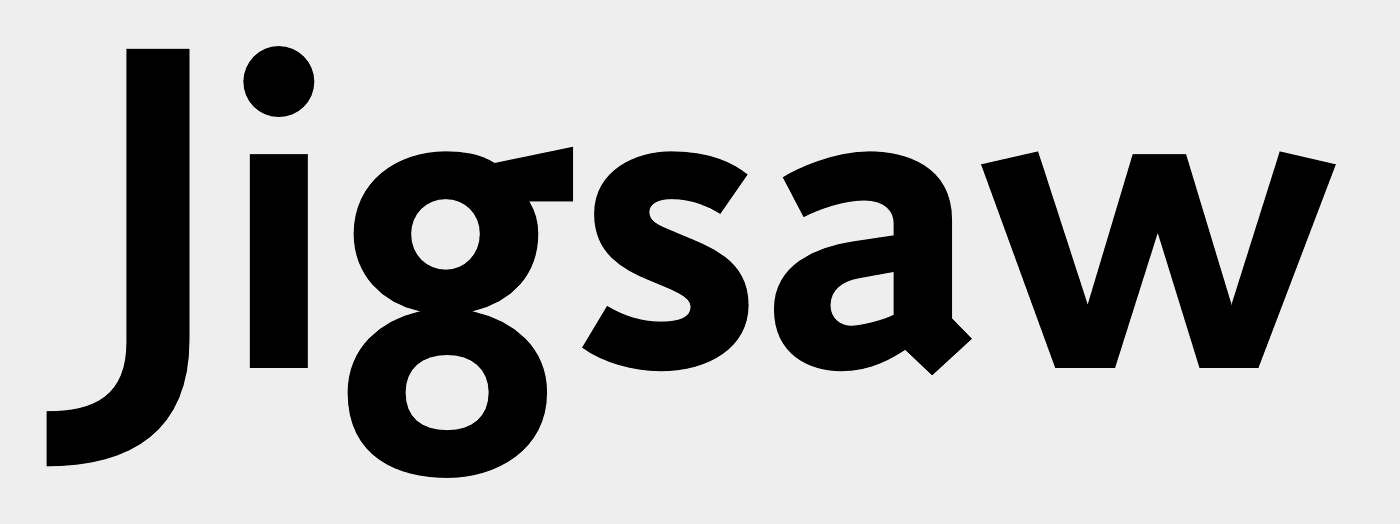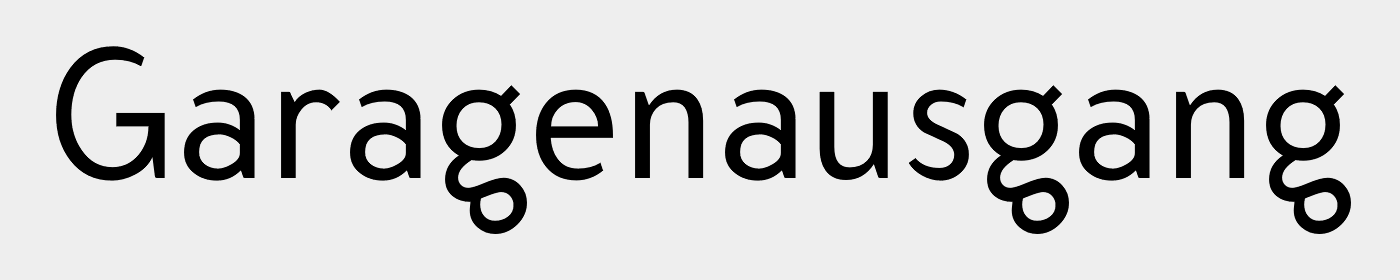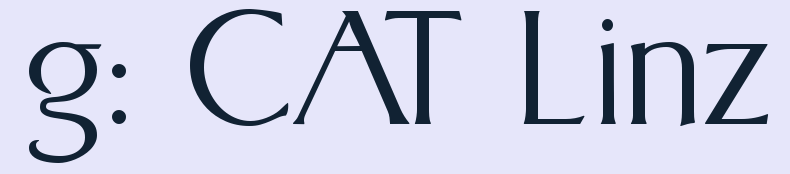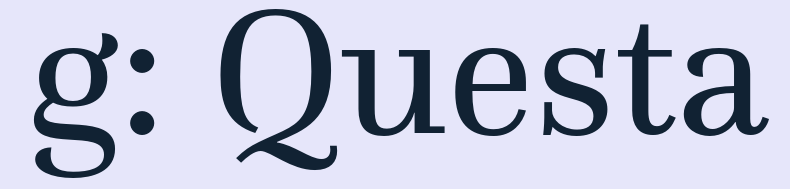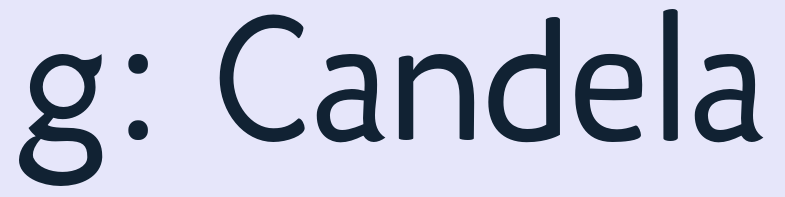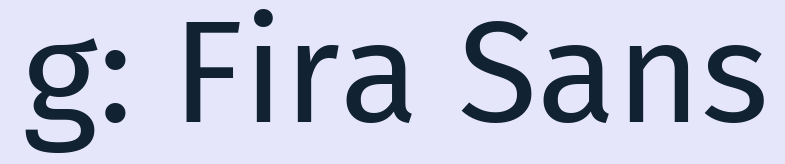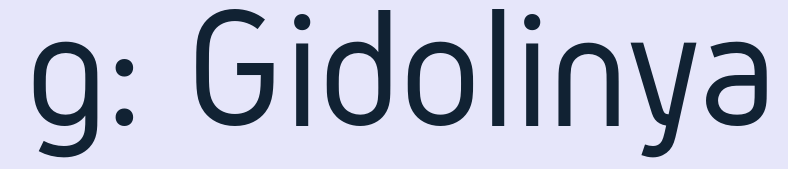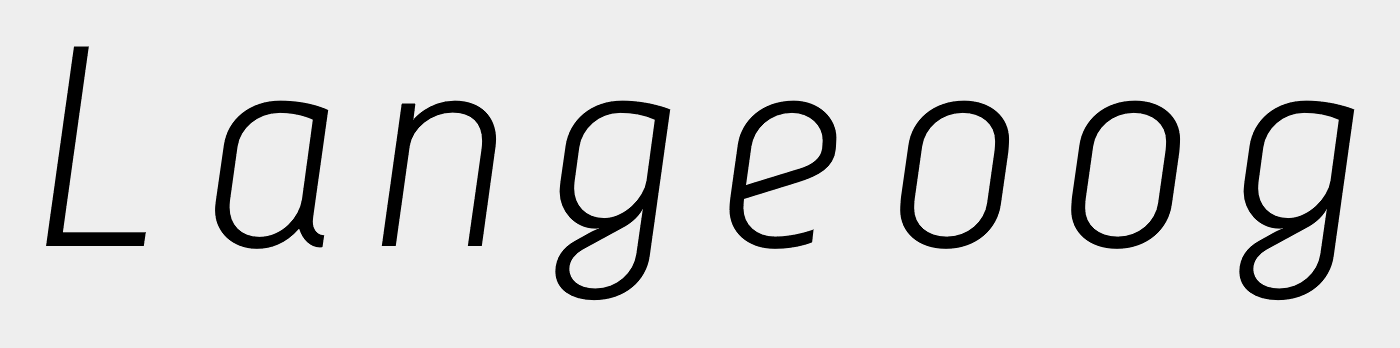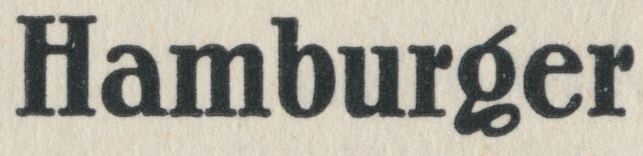
Bei der Questa denke ich immer an ein g, das ein Taxi herbei winkt. Und das Klint-g ist eine perspektivisch verzerrte Brille hochkant.
Dann noch ein paar aus meiner kleinen Liste kostenloser Schriften …
Hatten wir das Modell Beschworene Schlange eigentlich schon? :-?
Und noch ein paar andere: Modelle Krumme Brille, Oben Offen, Sans/Mono dreistöckig, Keine 9, Kein q,…
Nach Kursiven habe ich nicht besonders gesucht, aber vielleicht ist die Lato (»Brille verkehrt rum«) ja erwähnenswert.
Das ist die schmale und die schmale halbfette Epoche von Benjamin Krebs Nachf. Frankfurt/M. aus dem Jahr 1925.
Die erste von Paul Renner ist wohl klar, oder?
Eine Schrift mit einem sehr eigenartigen „g“ fiel mir vor geraumer Zeit auf der Netzseite der Werbeagentur Horaczek auf, von welcher man auch die Schrift „Wiener Norm“ laden kann.
Sie heißt auf der Seite „PrioriSanHoraczekRegular“ bzw. „PrioriAdaptet Regular“ und ich nehme an es handelt sich um eine umgebaute „Priori Sans“. Auch die Priori Sans hat ja schon ein etwas außergewöhnliches „g“ welches aber doch noch als solches erkennbar ist.